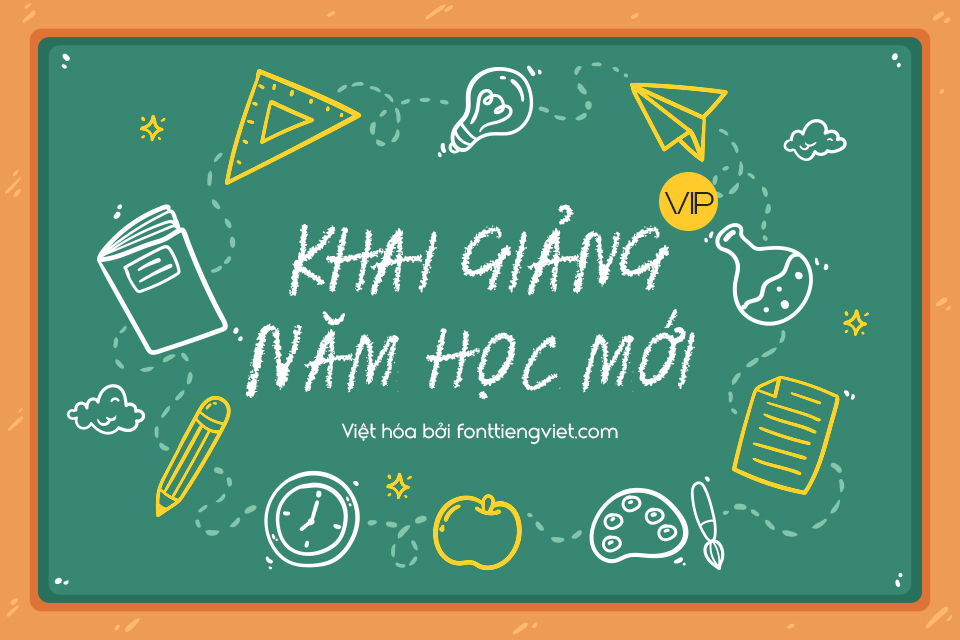
Font việt hóa 1FTV Bandem – Phấn
Giới thiệu về Font việt hóa 1FTV Bandem – Phấn
Trong môi trường học đường, việc tạo ra các tài liệu giảng dạy sinh động luôn là ưu tiên hàng đầu của các thầy cô giáo. Font việt hóa 1FTV Bandem – Phấn xuất hiện như một giải pháp hoàn hảo mang lại hơi thở của bảng đen lớp học vào các thiết kế số. Với đường nét mô phỏng nét phấn vẽ tay tự nhiên, Font Miễn Phí này giúp các bài giảng PowerPoint hoặc phiếu bài tập trở nên gần gũi và thân thiện hơn với học sinh. Bộ font đã được tối ưu hóa đầy đủ dấu tiếng Việt, đảm bảo không lỗi font khi gõ nội dung dài.
Đặc điểm nổi bật của phông chữ
Font việt hóa 1FTV Bandem – Phấn sở hữu phong cách vừa mộc mạc vừa đầy tính nghệ thuật. Các ký tự được mô phỏng theo cấu trúc viết tay không đồng nhất, tạo cảm giác như được viết trực tiếp bằng phấn trắng trên nền bảng xanh. Điều này giúp kích thích thị giác và sự hứng thú của người học, đặc biệt là các bạn nhỏ cấp tiểu học.
Ứng dụng Font việt hóa 1FTV Bandem – Phấn trong học tập
Ngoài việc dùng cho bài giảng, bạn có thể áp dụng Font việt hóa 1FTV Bandem – Phấn vào việc thiết kế thiệp mời họp phụ huynh, thực đơn căn tin hay các bảng thông báo nội quy lớp học. Sự linh hoạt của bộ chữ cho phép bạn sáng tạo không giới hạn trong các dự án phi lợi nhuận của nhà trường. Kết hợp font này với các icon vẽ tay sẽ tạo nên một tổng thể thiết kế vô cùng chuyên nghiệp và bắt mắt.
Hướng dẫn sử dụng hiệu quả
Để đạt hiệu quả thẩm mỹ cao nhất, hãy sử dụng font chữ này trên nền tối hoặc các hình ảnh có texture bảng đen. Tránh sử dụng font cho các văn bản hành chính quá trang trọng để duy trì đúng tinh thần sáng tạo của nó.
Kết luận về bộ font độc đáo